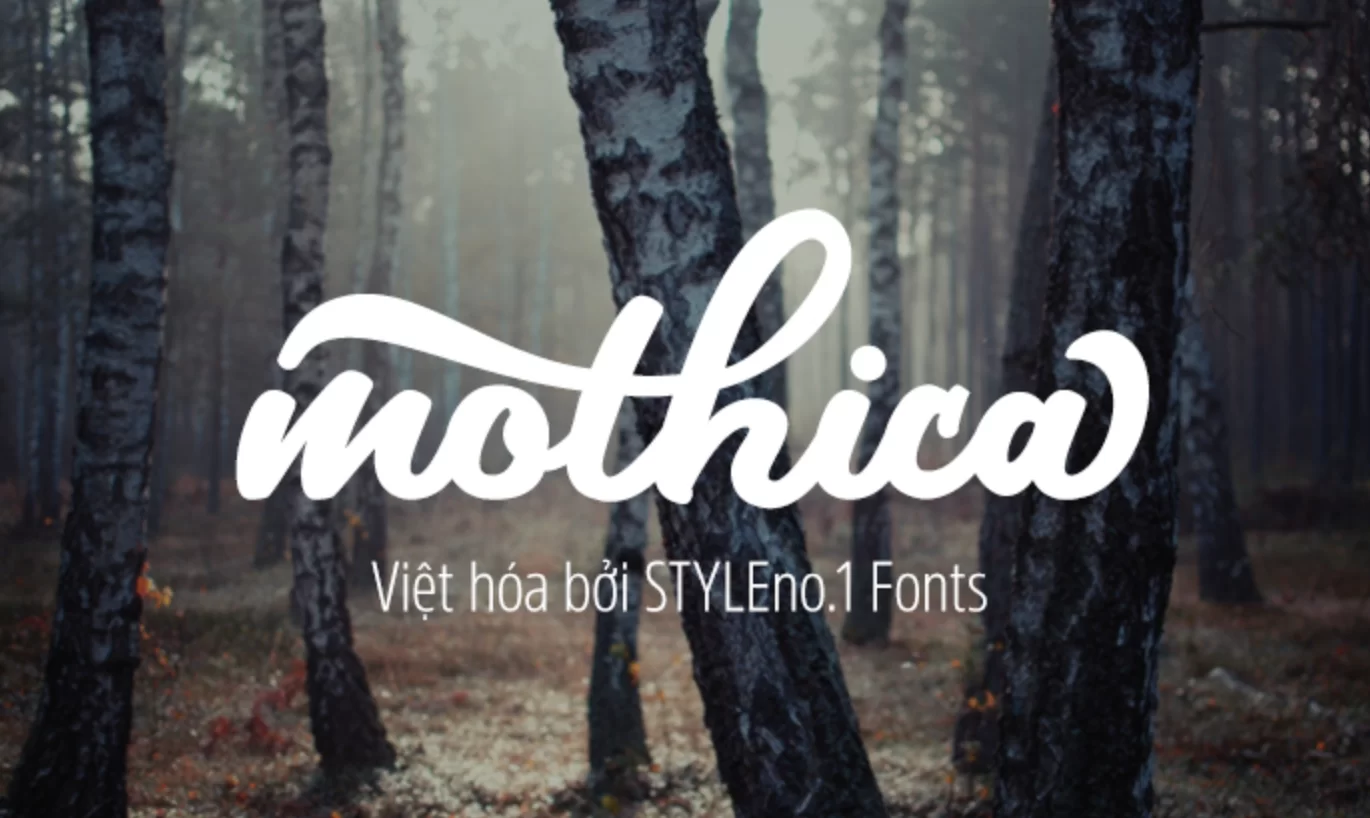
Mothica Bold là một Script đẹp, Nó phù hợp để thiết kế thiệp mời đám cưới, thiệp chúc mừng, T-Shirt, Logo hoặc bất kỳ thiết kế nào mà bạn tạo ra với một bộ đầy đủ các ký tự chuẩn, Alternates, dấu chấm câu và glyphs quốc tế.
Nhà thiết kế: Olexstudio
Nhà phát hành: Olexstudio